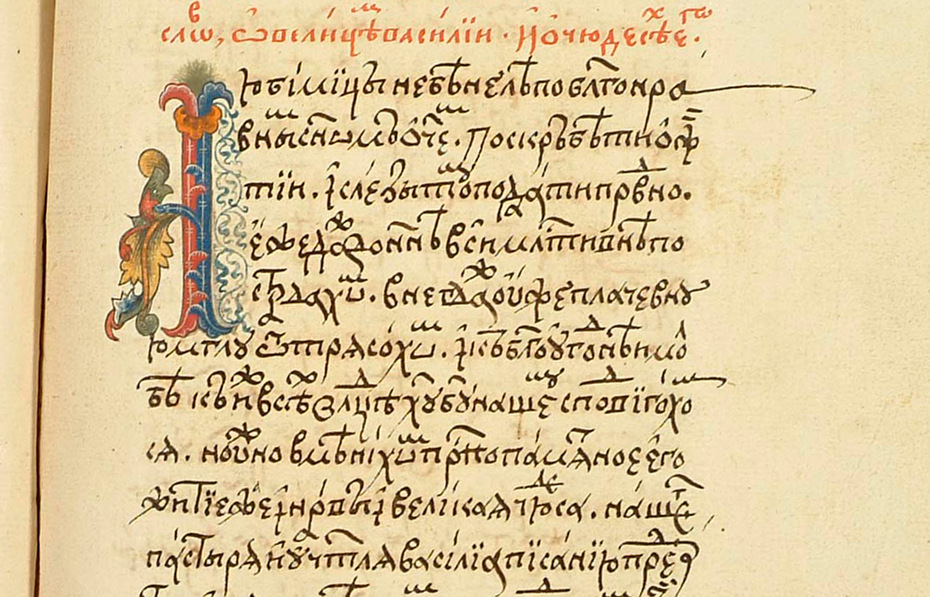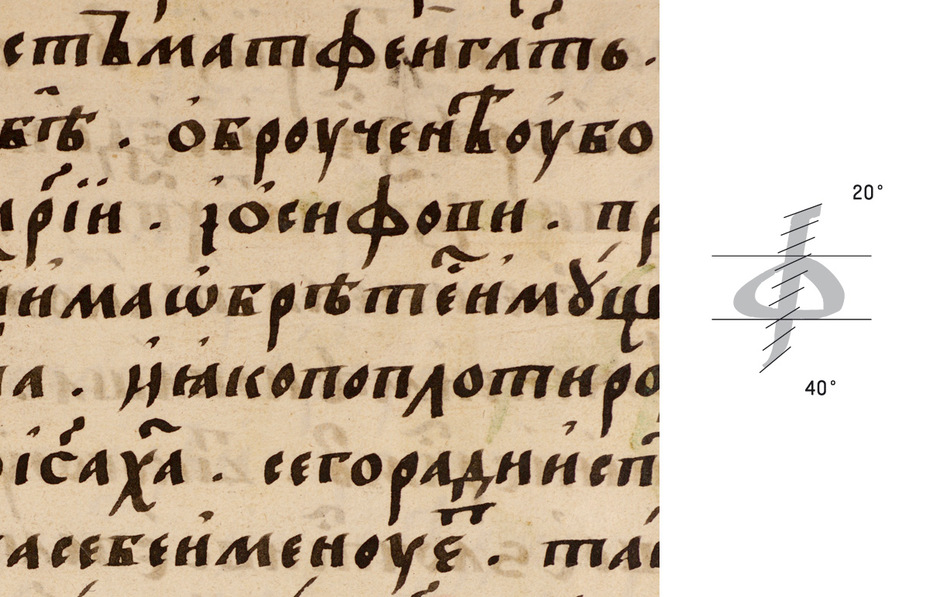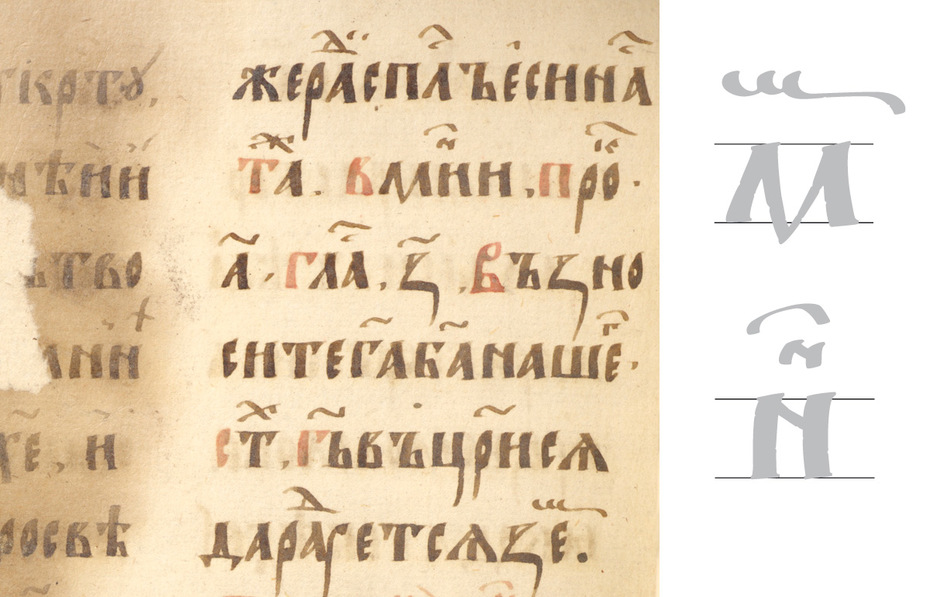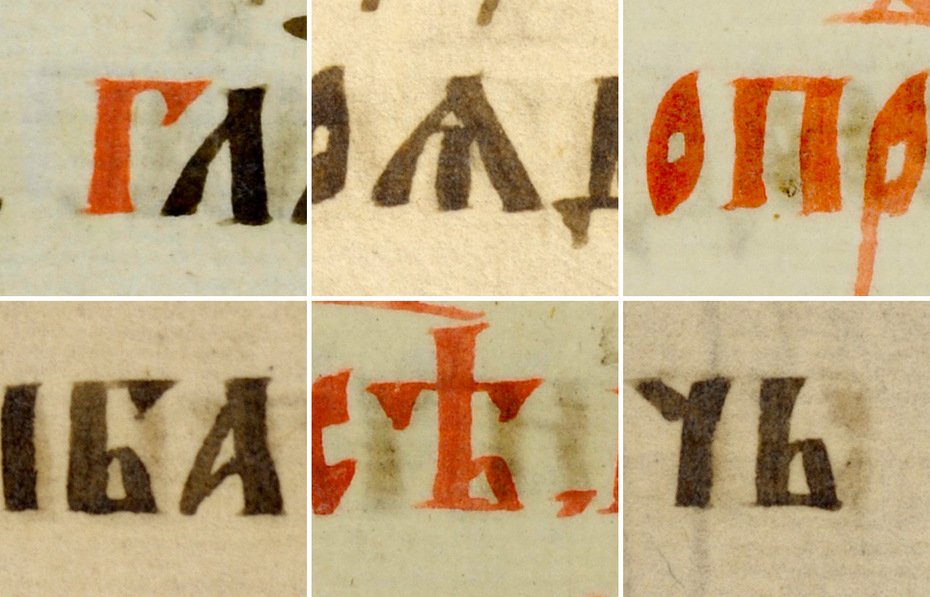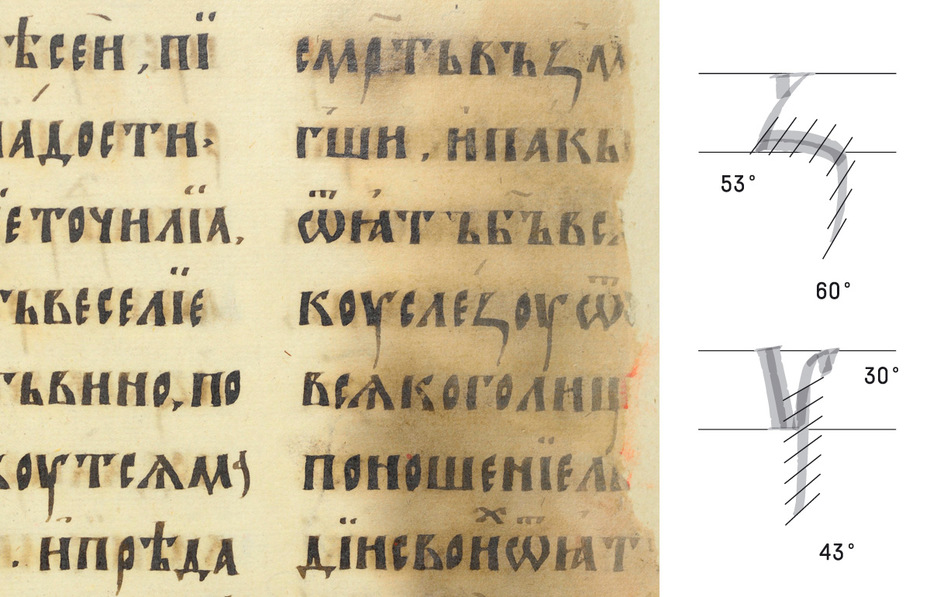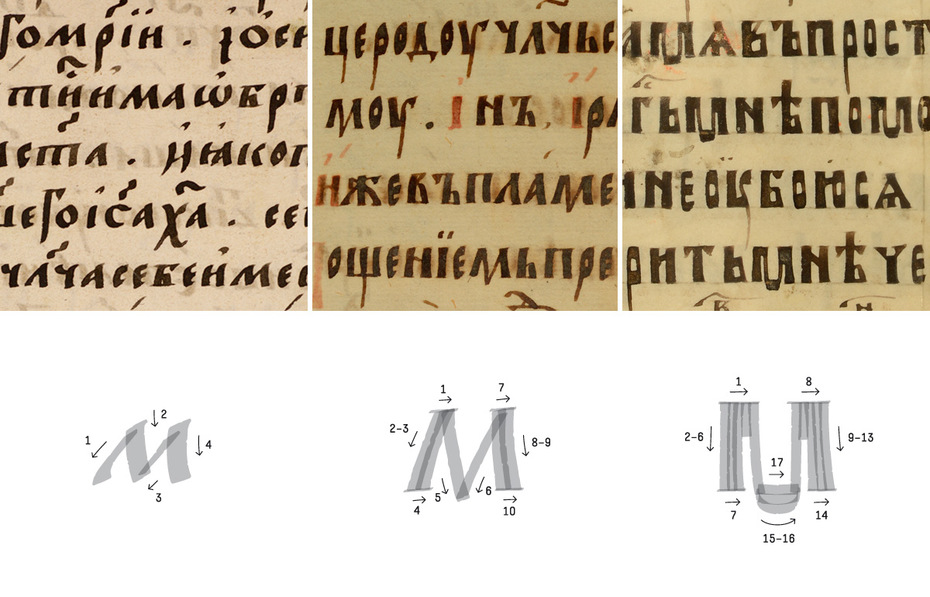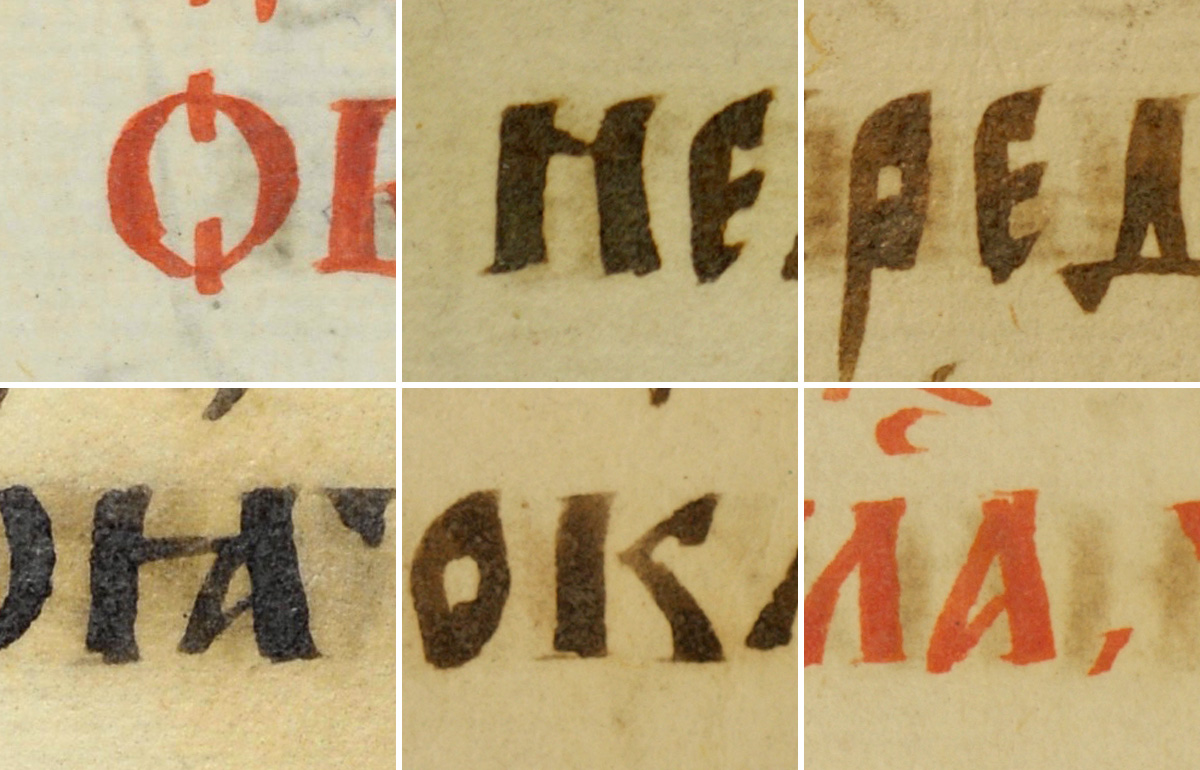
О двух техниках древнерусской каллиграфии
Ла­ти­ни­це по­вез­ло — ис­сле­до­ва­ния Эд­вар­да Джон­сто­на и его уче­ни­ков про­дви­ну­ли раз­ви­тие шриф­тов в XX ве­ке. Тех­ни­ка же ки­рил­лов­ской кал­ли­гра­фии изу­че­на не так ши­ро­ко. Ста­тья, ко­то­рую мы пред­став­ля­ем, от­ча­сти вос­пол­ня­ет этот про­бел. Рас­смат­ри­вая ин­те­рес­ней­шие ис­точ­ни­ки, ав­то­ры рас­кры­ва­ют не­обыч­ную струк­ту­ру книж­но­го уста­ва и вво­дят в тер­ми­но­ло­гию по­ня­тие со­став­но­го пись­ма.
о­гда речь за­хо­дит о тех­ни­ке древ­не­рус­ской кал­ли­гра­фии, быть мо­жет, пер­вым при­хо­дит на ум рас­про­странён­ное ут­вер­жде­ние о ри­со­ван­ном ха­рак­те­ре устав­ных по­чер­ков. Этот те­зис то и де­ло воз­ни­ка­ет на стра­ни­цах кал­ли­гра­фи­че­ских учеб­ни­ков, в ра­бо­тах па­лео­гра­фов и в се­те­вых дис­кус­си­ях, хо­тя ни­где не под­твер­жда­ет­ся ни раз­бо­ром дук­тов пись­ма, ни во­об­ще ка­ким-ли­бо опи­са­ни­ем приёмов ра­бо­ты сред­не­ве­ко­вых кни­го­пис­цев. Как это ни па­ра­док­саль­но, во­прос тех­ни­ки об­хо­дят сто­ро­ной и кал­ли­гра­фы, и па­лео­гра­фы, огра­ни­чи­ва­ясь обыч­но су­хой ха­рак­те­ри­сти­кой ти­пов пись­ма. Устав — пря­мой, ар­хи­тек­тур­ный и гео­мет­рич­ный, по­лу­устав — на­клон­ный, ме­нее пра­виль­ный и бо­лее бег­лый. Из этих опи­са­ний пер­вых рус­ских по­чер­ков не по­нят­ны ни осо­бен­но­сти ра­бо­ты пис­ца, ни ха­рак­тер и ко­ли­че­ство дви­же­ний, ис­поль­зу­е­мых при со­зда­нии букв, ни то­, на­ко­нец, по­че­му по­лу­устав пи­сал­ся бы­стрее.
По­это­му, за­те­вая три го­да на­зад ис­сле­до­ва­ние гра­фи­ки древ­не­рус­ских книг, мы ста­ви­ли сво­ей це­лью преж­де все­го опре­де­лить тех­ни­ку ис­пол­не­ния устав­ных и по­лу­устав­ных по­чер­ков XIV–XVI ве­ков, по­нять, как эта тех­ни­ка со­от­но­сит­ся с тем, что из­вест­но нам о за­пад­ной кал­ли­гра­фии, вы­явить дук­ты пись­ма, и в кон­це кон­цов про­ве­рить, со­от­вет­ству­ет ли дей­стви­тель­но­сти ут­вер­жде­ние о ри­со­ван­ном ха­рак­те­ре уста­ва. То, что в ито­ге на­ми об­на­ру­же­но, в зна­чи­тель­ной сте­пе­ни ме­ня­ет пред­став­ле­ние о древ­не­рус­ской кал­ли­гра­фии. Мы мо­жем го­во­рить об ис­поль­зо­ва­нии древ­не­рус­ски­ми ма­сте­ра­ми по мень­шей ме­ре двух тех­ник пись­ма, од­на из ко­то­рых яв­ля­ет­ся если не уни­каль­ной, то до­ста­точ­но ред­кой (воз­мож­но, не­что по­хо­жее встре­ча­ет­ся лишь в гре­че­ских и ла­тин­ских за­го­ло­воч­ных над­пи­сях). Эта тех­ни­ка по­тре­бо­ва­ла и со­по­став­ле­ния её с дру­ги­ми спо­со­ба­ми со­зда­ния букв, и уточ­не­ния су­ще­ству­ю­щей тер­ми­но­ло­гии. Но обо всём по по­ряд­ку.
Преж­де чем мы обра­тим­ся не­по­сред­ствен­но к тех­ни­ке кал­ли­гра­фии, не­об­хо­ди­мо ска­зать не­сколь­ко слов о раз­ви­тии древ­не­рус­ских форм пись­ма в XX–XXI ве­ках и о тех све­де­ни­ях о тех­ни­ке, что мож­но най­ти в ра­бо­тах па­лео­гра­фов и кал­ли­гра­фов. Ведь имен­но ис­то­ри­че­ская кан­ва XX ве­ка во мно­гом опре­де­ли­ла то, что о древ­не­рус­ской кал­ли­гра­фии из­вест­но не так мно­го.
Ти­по­гра­фи­че­ское и кал­ли­гра­фи­че­ское воз­ро­жде­ние, ха­рак­тер­ное для Ев­ро­пы и США ру­бе­жа XIX–XX ве­ков и свя­зан­ное в об­ла­сти кал­ли­гра­фии с име­на­ми Эд­вар­да Джон­сто­на (Ан­глия), Ру­доль­фа Ко­ха (Гер­ма­ния) и Ру­доль­фа фон Ла­ри­ша (Ав­стрия), кос­ну­лось Рос­сии лишь от­ча­сти. Если на За­па­де этот пе­ри­од озна­ме­но­ван как раз вто­рым от­кры­ти­ем тех­ни­ки ши­ро­ко­ко­неч­но­го пе­ра и про­бу­жде­ни­ем ин­те­ре­са к ис­то­ри­че­ской кал­ли­гра­фии (преж­де все­го речь идёт, ко­неч­но, об ис­сле­до­ва­ни­ях Эд­вар­да Джон­сто­на), то при­ме­ни­тель­но к Рос­сии мы мо­жем го­во­рить лишь о воз­ро­жде­нии ис­то­ри­че­ских шриф­то­вых форм в ак­ци­ден­ции, в ри­со­ван­ных шриф­тах и в не­ко­то­рой сте­пе­ни в шриф­тах на­бор­ных, тек­сто­вых, но не в кал­ли­гра­фии. Вто­ро­го ро­жде­ния ши­ро­ко­ко­неч­но­го пе­ра в Рос­сии в на­ча­ле XX ве­ка не про­изо­шло.
Рус­ские ху­дож­ни­ки это­го пе­ри­о­да ак­тив­но ра­бо­та­ли с древ­не­рус­ской тра­ди­ци­ей, об­ра­ща­лись к до­пет­ров­ским ти­пам пись­ма: уста­ву, по­лу­уста­ву, вя­зи и ско­ро­пи­си. Но всё это бы­ли ри­со­ван­ные фор­мы. Да­же про­стые тек­сто­вые по­чер­ки ча­ще все­го ри­со­ва­лись, а не пи­са­лись. И хо­тя ин­тер­пре­та­ции ис­то­ри­че­ско­го на­сле­дия бы­ли гра­фи­че­ски чрез­вы­чай­но изоб­ре­та­тель­ны и тех­ни­че­ски ис­кус­ны — будь то про­стые вер­сии по­лу­уста­ва или за­мыс­ло­ва­тые фор­мы букв вя­зи в ду­хе мо­дер­на, — во­прос тех­ни­ки, а тем бо­лее ори­ги­наль­ной древ­не­рус­ской тех­ни­ки, ху­дож­ни­ка­ми не ста­вил­ся. Сто­ит как не­ко­то­рое ис­клю­че­ние на об­щем фо­не от­ме­тить са­мо­быт­ные ско­ро­пис­ные ра­бо­ты пи­са­те­ля Алек­сея Ре­ми­зо­ва — од­ну из не­мно­гих по­пы­ток пи­сать, а не ри­со­вать ис­то­ри­че­ские по­чер­ки. Ре­ми­зов за­ни­мал­ся изу­че­ни­ем древ­них сла­вян­ских гра­мот и да­же в своём бы­то­вом пись­ме ис­поль­зо­вал гра­фи­ку ско­ро­пи­си.
Ши­ро­ко­ко­неч­ное пе­ро на­чи­на­ет ак­тив­но ис­поль­зо­вать­ся оте­че­ствен­ны­ми ху­дож­ни­ка­ми толь­ко в кон­це 1950-х — на­ча­ле 1960-х го­дов. В основ­ном это бы­ло свя­за­но с вли­я­ни­ем ев­ро­пей­ской кал­ли­гра­фии. К это­му же вре­ме­ни сто­ит от­не­сти и не­ко­то­рое воз­ро­жде­ние ин­те­ре­са к фор­мам до­пет­ров­ской ки­рил­ли­цы. Од­на­ко боль­шин­ство по­яв­ляв­ших­ся шриф­то­вых по­со­бий и книг по кал­ли­гра­фии рас­смат­ри­ва­ли глав­ным об­ра­зом ис­то­рию ла­тин­ско­го шриф­та и пред­ла­га­ли схе­мы на­пи­са­ния ки­рил­лов­ских букв в ла­тин­ской гра­фи­ке (ки­рил­ли­ца в ита­льян­ском кур­си­ве, ки­рил­ли­ца в рим­ском мо­ну­мен­таль­ном пись­ме и т. д.). То есть за­креп­лял­ся прин­цип адап­та­ции. И если ра­бо­та ши­ро­ко­ко­неч­ным пе­ром в ла­тин­ских по­чер­ках рас­смат­ри­ва­лась по­дроб­но, то рус­ско­му пись­му в по­доб­ных из­да­ни­ях от­во­ди­лось, как пра­ви­ло, все­го па­ра аб­за­цев, а дук­ты его не рас­смат­ри­ва­лись во­все. Та­кое по­ло­же­ние ве­щей со­хра­ня­лось вплоть до по­след­не­го вре­ме­ни. Ис­клю­че­ние — учеб­ни­ки П. П. Чо­бить­ко и Д. И. Пет­ров­ско­го, в ко­то­рых пред­став­ле­ны ав­тор­ские учеб­ные ва­ри­ан­ты уста­ва и по­лу­уста­ва (а у Дмит­рия Ильи­ча так­же ско­ро­пи­си и вя­зи). В про­шлом го­ду вы­шел аль­бом А. В. Сан­ни­ко­ва и Ю. И. Ко­вер­дя­е­ва, в ко­то­ром про­из­во­дит­ся раз­бор дук­тов пись­ма трёх ис­то­ри­че­ских ру­ко­пи­сей.
В це­лом со­вре­мен­ные кал­ли­гра­фы в от­ли­чие от ма­сте­ров на­ча­ла про­шло­го ве­ка пред­по­чи­та­ют не ри­со­вать, а пи­сать ши­ро­ко­ко­неч­ным пе­ром и устав, и по­лу­устав, и да­же вязь. Но, не­смот­ря на то что боль­шин­ством ма­сте­ров рус­ские по­чер­ки пи­шут­ся, сре­ди кал­ли­гра­фов встре­ча­ет­ся (а в па­лео­гра­фии яв­ля­ет­ся рас­про­странён­ным) убе­жде­ние, что устав — ри­со­ван­ный тип пись­ма.
Это убе­жде­ние, ве­ро­ят­но, по­яви­лось под вли­я­ни­ем ра­бот па­лео­гра­фов, в ко­то­рых на­чи­ная с кни­ги 1909 го­да Р. Ф. Бран­д­та не­од­но­крат­но го­во­рит­ся о ри­со­ван­ном ха­рак­те­ре уста­ва. Так, Ро­ман Фё­до­ро­вич пишет: «Уставъ, это — бук­вы по­хожiя на те­пе­реш­нiя пе­чат­ныя, по­чти квад­рат­ной фор­мы (при­бли­зи­тель­но та­кой же ши­ри­ны, какъ и дли­ны), ко­то­рыя при­томъ тща­тель­но вы­ри­со­вы­ва­лись». По­сколь­ку дук­ты ис­то­ри­че­ских ки­рил­лов­ских по­чер­ков не раз­би­ра­ют­ся ни в од­ном па­лео­гра­фи­че­ском ис­сле­до­ва­нии, мож­но пред­по­ло­жить, что при­чи­на та­кой ха­рак­те­ри­сти­ки, во-пер­вых, в ста­тич­ном и пра­виль­ном об­ли­ке уста­ва, а во-вто­рых, в от­сут­ствии зна­ний о тех­ни­ке кал­ли­гра­фии. На­при­мер, аб­со­лют­ное боль­шин­ство па­лео­гра­фов не от­ли­ча­ет тех­ни­ку ши­ро­ко­ко­неч­но­го пе­ра от тех­ни­ки остро­ко­неч­но­го и ак­тив­но ис­поль­зу­ет тер­мин «на­жим» в опи­са­нии уста­ва и по­лу­уста­ва, хо­тя эти по­чер­ки пи­са­лись ши­ро­ким пе­ром и ни о ка­ких на­жи­мах в дан­ном слу­чае го­во­рить не­льзя. Спра­вед­ли­во­сти ра­ди нуж­но от­ме­тить, что в ла­тин­ской па­лео­гра­фии изу­че­ние дви­же­ния при пись­ме и вы­яв­ле­ние дук­тов на­ча­лось то­же да­ле­ко не сра­зу (толь­ко в кон­це 30-х го­дов XX ве­ка бла­го­да­ря Жа­ну Мал­ло­ну).
Но вер­нём­ся к так на­зы­ва­е­мо­му «ри­со­ван­но­му уста­ву». По­жа­луй, ча­ще дру­гих эпи­тет «ри­со­ван­ный» встре­ча­ет­ся в ра­бо­тах Л. М. Ко­стю­хи­ной. На­при­мер, о по­зд­нем уста­ве она пи­шет сле­ду­ю­щее: «Устав рус­ских ру­ко­пи­сей ру­бе­жа XIV–XV ве­ков — это ри­со­ван­ное, кал­ли­гра­фи­че­ски чёт­кое рит­мич­ное пись­мо с пря­мо сто­я­щи­ми в стро­ке бук­ва­ми, изящ­но су­жен­ны­ми и не­сколь­ко вы­тя­ну­ты­ми по вер­ти­ка­ли». Од­на­ко на­име­но­ва­ние «ри­со­ван­ных» по­лу­ча­ют у неё не толь­ко устав­ные по­чер­ки XIV–XV ве­ков, но и не­ко­то­рые за­мыс­ло­ва­тые по­лу­устав­ные XV–XVII ве­ков, про­ти­во­по­став­ля­ясь про­стым по­лу­устав­ным. На­при­мер, по­чер­ки Го­ду­нов­ской псал­ты­ри. «Ука­зан­ные чер­ты по­чер­ков ру­ко­пи­сей ста­риц­ко-мо­сков­ско­го ком­плек­са про­яв­ля­ют­ся и в по­лу­уста­ве Го­ду­нов­ских псал­ты­рей…по­лу­устав всех пя­ти ру­ко­пис­ных псал­ты­рей, хра­ня­щих­ся в ГИМ, но­сит ещё бо­лее обоб­щён­ный, ри­со­ван­ный ха­рак­тер, чем в кни­гах ста­риц­ко-мо­сков­ской груп­пы». В то же вре­мя не яс­но, го­во­рят ли Ко­стю­хи­на и дру­гие па­лео­гра­фы имен­но о тех­ни­ке ис­пол­не­ния или они ис­поль­зу­ют эпи­тет «ри­со­ван­ный» для обо­зна­че­ния наи­бо­лее вы­чур­ных, ма­нер­ных по­чер­ков. Объ­яс­не­ние сло­ва «ри­со­ван­ный» при­ме­ни­тель­но к уста­ву есть толь­ко в ра­бо­те Д. И. Пет­ров­ско­го, со­глас­но мне­нию ко­то­ро­го «шрифт под­час не столь­ко пи­са­ли, сколь­ко ри­со­ва­ли пе­ром мень­шей ши­ри­ны».
Что же та­кое ри­со­ван­ный шрифт? В оте­че­ствен­ной ли­те­ра­ту­ре по па­лео­гра­фии и кал­ли­гра­фии мы не на­хо­дим опре­де­ле­ния пись­ма и ри­со­ва­ния, как двух спо­со­бов со­зда­ния букв, по­это­му вы­ну­жде­ны обра­тить­ся к тер­ми­но­ло­гии, раз­ра­бо­тан­ной за­ру­беж­ны­ми ав­то­ра­ми. Наи­бо­лее яс­ны­ми нам пред­став­ля­ют­ся опре­де­ле­ния Эд­вар­да Ка­ти­ча, ко­то­рые он даёт в кни­ге The origin of the serif:
Вме­сто ан­глий­ско­го сло­ва lettering в на­шей ста­тье мы ис­поль­зу­ем по­нят­ные рус­ские ана­ло­ги «ри­со­ва­ние букв», «ри­со­ван­ный шрифт» — бы­ло бы стран­но го­во­рить, что рус­ские сред­не­ве­ко­вые пис­цы за­ни­ма­лись лет­те­рин­гом. Од­на­ко в дру­гих слу­ча­ях мы до­пус­ка­ем упо­треб­ле­ние ан­глий­ско­го за­им­ство­ва­ния. На­при­мер, от­сут­ствие в рус­ском язы­ке сло­ва, ко­то­рое озна­ча­ло бы шрифт, вы­пол­нен­ный лю­бым спо­со­бом кро­ме на­бо­ра и пись­ма, вы­ну­жда­ет вре­мя от вре­ме­ни ис­поль­зо­вать «лет­те­ринг». Упо­треб­ле­ние в дан­ном слу­чае про­сто­го «шрифт» ас­со­ци­и­ро­ва­лось бы ис­клю­чи­тель­но со шриф­том на­бор­ным.